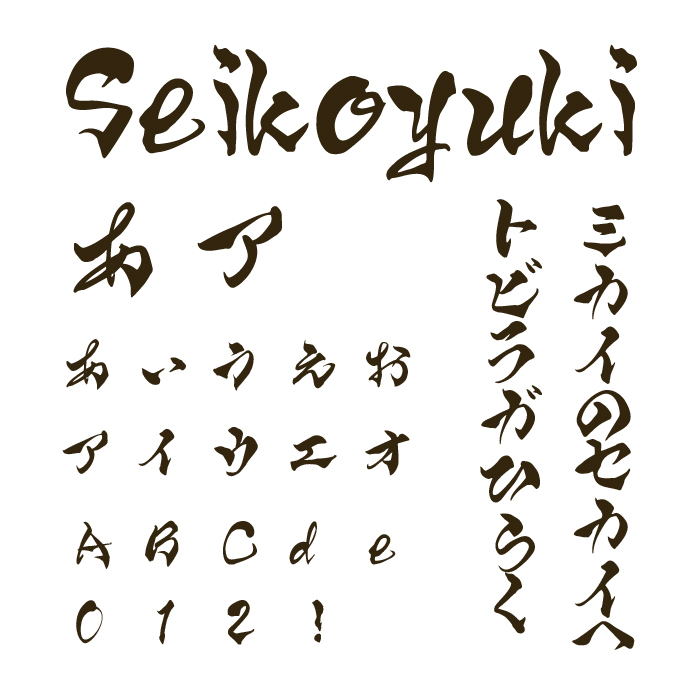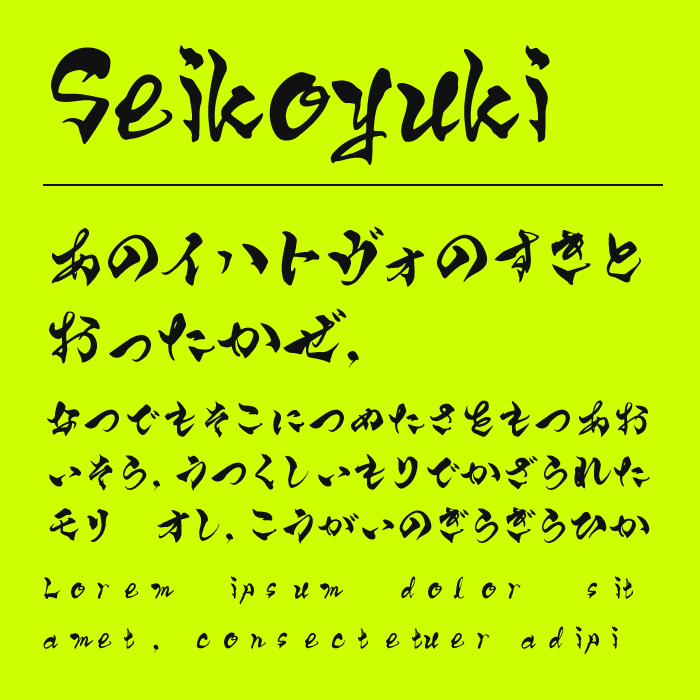
Seikoyuki筆文字フォントは、筆でダイナミックにざっくりと書いたようスピード感と勢いを強く感じる筆文字フォントです。
筆跡の荒々しさが力強さを生み出し、ライブ感や情熱的な雰囲気を演出できます。飲食系や和風イベントなど、視覚的なインパクトと個性を求める場面におすすめの、情熱的で感情豊かなフォントです。
現在は漢字の収録がありませんが、今後のアップデートで追加されるとのことです。
フォントの文字見本
収録文字は、ひらがな・カタカナ・アルファベット・数字・記号が収録。